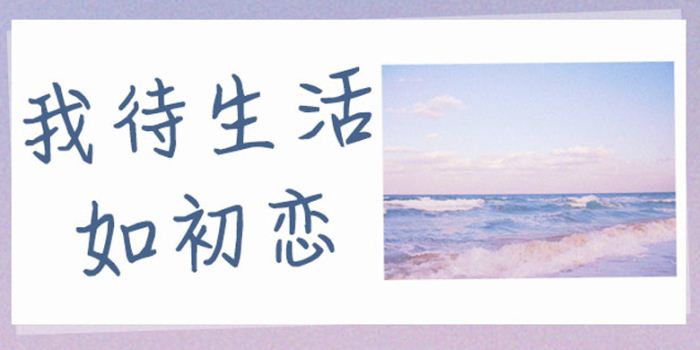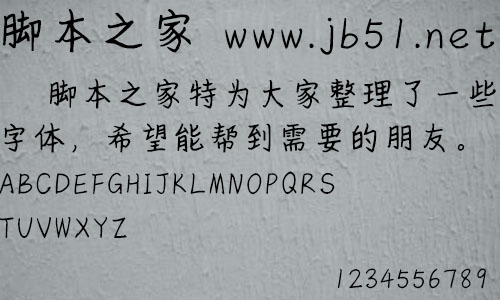
方正手跡-我待生活如初戀由方正字庫王航設(shè)計(jì)師出品的藝術(shù)字體,該字整體瘦高,字面較大識(shí)別度較高。筆畫布白均勻,視覺良好,適合應(yīng)用于藝術(shù)設(shè)計(jì)、平面宣傳設(shè)計(jì)、網(wǎng)頁設(shè)計(jì),書法等領(lǐng)域。
我待生活如初戀是一款簡單雅致的手寫體。該字體整體瘦高,字面較大識(shí)別度較高。筆畫布白均勻,視覺良好。適用于文藝類和可愛類的書刊、品牌廣告和產(chǎn)品包裝設(shè)計(jì),以及社交網(wǎng)絡(luò)的個(gè)性化用字。。